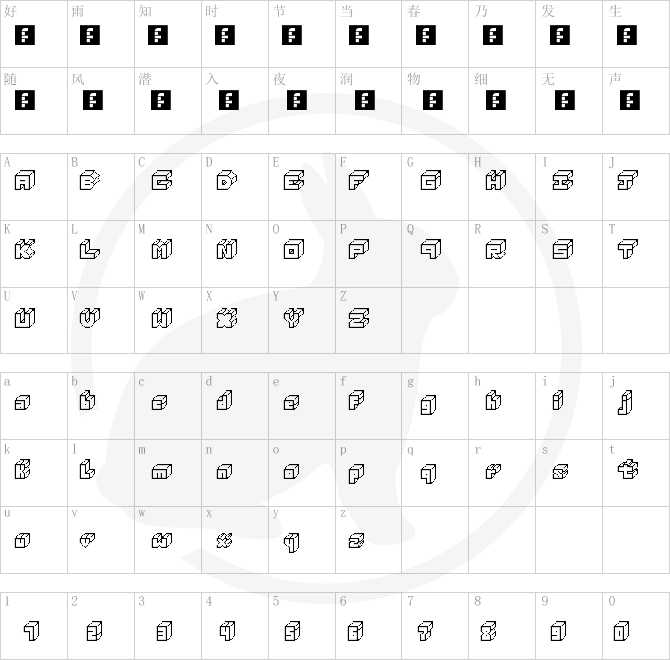
3D Thirteen Pixel Fonts.ttf字体下载,这款字体结构工整、笔画清晰,兼顾美观与易读性,适用于标题、正文、海报、包装、LOGO 等多种场景。字形优雅稳定,风格百搭耐看,适配日常排版与创意设计,让文字呈现更舒适、更具质感。3D Thirteen Pixel Fonts.ttf字体下载一笔一画,皆是细节,以均衡的比例、流畅的线条打造舒适视觉体验,字形端正大气,风格简约现代。无论是商业设计、品牌宣传还是日常排版,都能轻松驾驭,让文字更有格调与力量。3D Thirteen Pixel Fonts.ttf字体下载字体下载。
“3D Thirteen Pixel Fonts” is based on “Thirteen Pixel Fonts” by “30100flo” (http://fontstruct.com/fontstructors/30100flo)